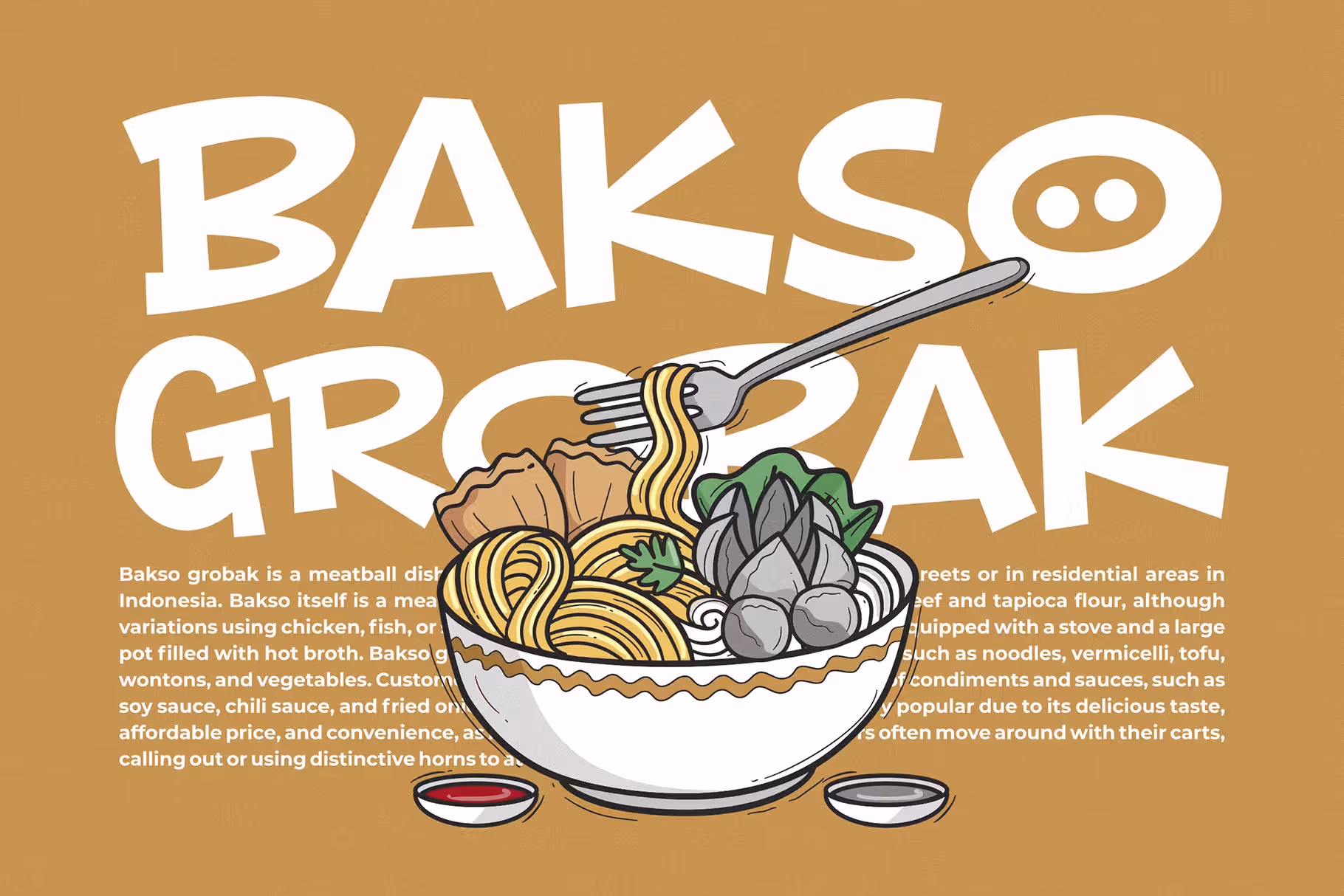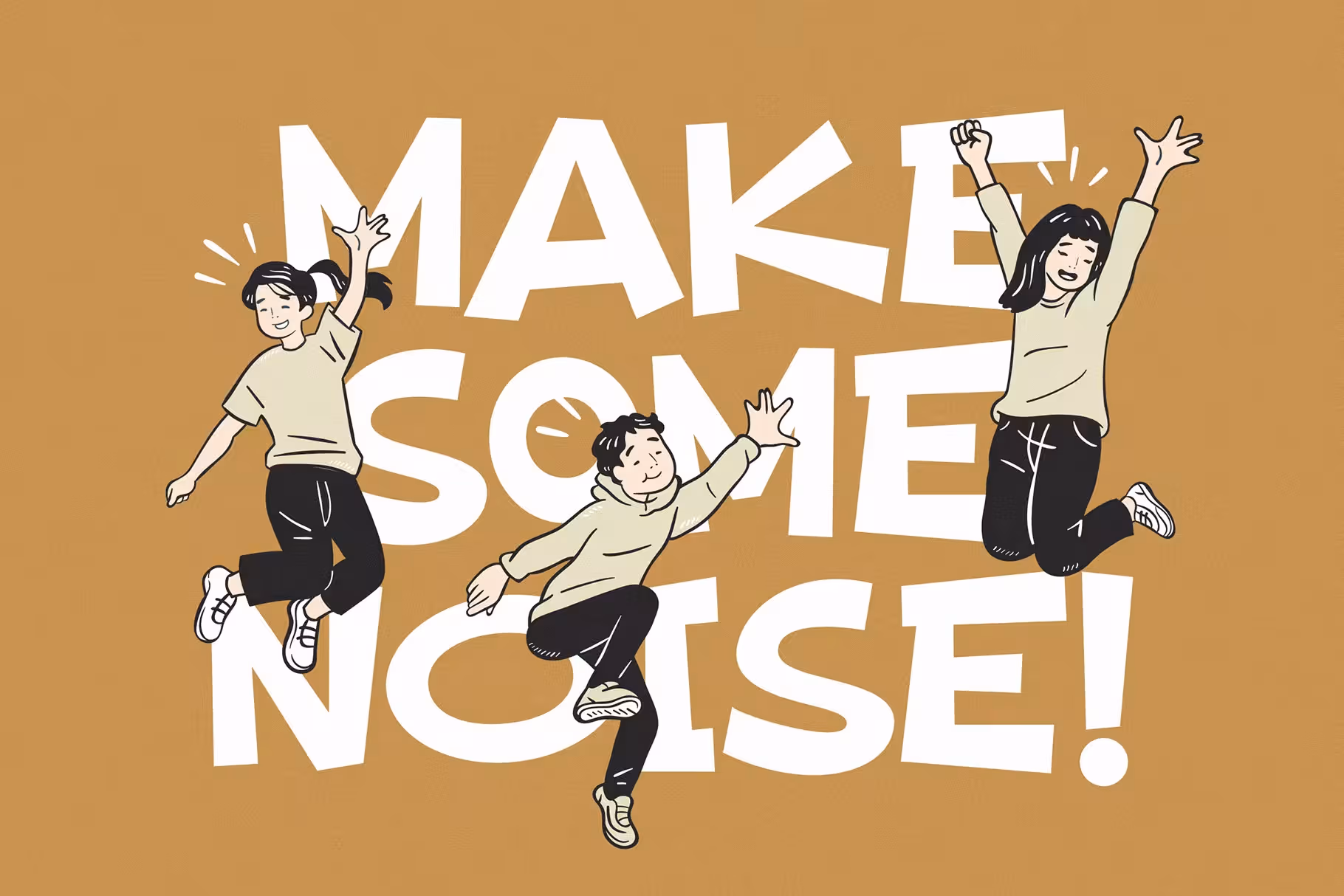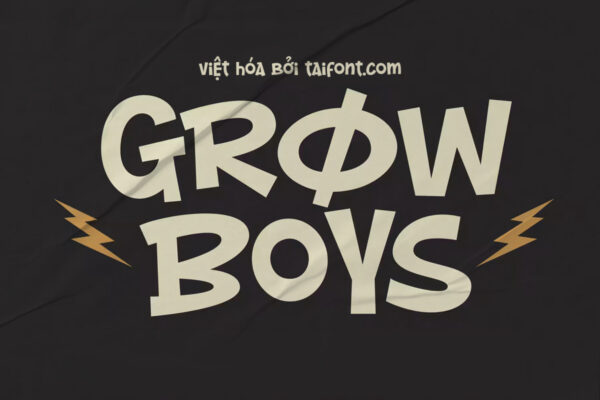
Giới thiệu về Font TF Grow Boys Việt hóa
TF Grow Boys Việt hóa là một font chữ trang trí nổi bật với thiết kế đậm đặc, độc đáo và đầy cá tính. Font này mang đến vẻ ngoài mạnh mẽ, ấn tượng và cực kỳ thu hút, gợi cảm giác về sự táo bạo, khác biệt và một chút nổi loạn, lý tưởng để tạo điểm nhấn thị giác mạnh mẽ và gây chú ý ngay lập tức.
Với đặc điểm thiết kế độc đáo, góc cạnh mạnh mẽ và khả năng tạo hiệu ứng thị giác ấn tượng, Grow Boys là lựa chọn hoàn hảo cho các ấn phẩm muốn truyền tải sự nổi bật và phong cách:
- Thiết kế gây chú ý: Hoàn hảo để sử dụng trên poster, banner, áp phích, hoặc bất kỳ ấn phẩm quảng cáo nào cần sự chú ý tối đa. Nét chữ to, đậm và độc đáo của font giúp thông điệp của bạn nổi bật, dễ đọc và truyền tải một cách hiệu quả ngay từ cái nhìn đầu tiên.
- Thiết kế thời trang và đường phố: Lý tưởng cho thương hiệu thời trang, phụ kiện, hoặc các ấn phẩm truyền thông liên quan đến văn hóa đường phố, giải trí. Font này giúp tạo dấu ấn cá nhân, sự phá cách và độc đáo cho thương hiệu.
- Thiết kế game và truyền thông: Phù hợp cho logo game, tiêu đề, hoặc các ấn phẩm quảng bá các tựa game, phim ảnh, hoặc sự kiện muốn tạo không khí kịch tính, lôi cuốn và đầy thách thức.
- Thiết kế nhận diện thương hiệu: Có thể dùng cho logo hoặc bộ nhận diện thương hiệu của các công ty, doanh nghiệp muốn truyền tải sự mạnh mẽ, cá tính và sự khác biệt.
Với TF Grow Boys Việt hóa, bạn có thể dễ dàng thổi hồn mạnh mẽ, sự độc đáo và cá tính vào các thiết kế, tạo ra những sản phẩm không chỉ đẹp mắt mà còn cực kỳ ấn tượng và có khả năng thu hút sự chú ý tối đa.